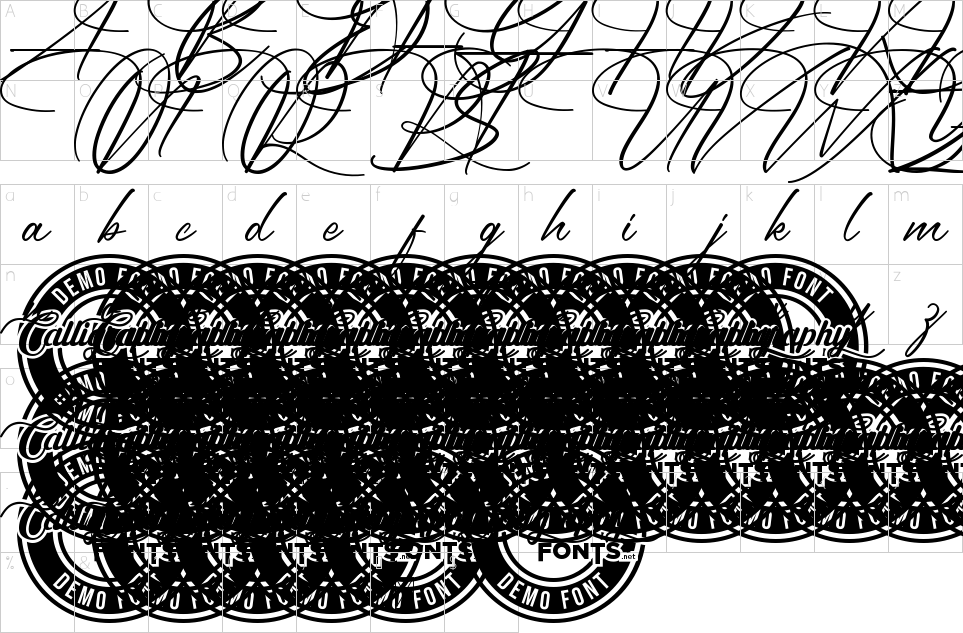
Glamour Line Font
Descubra a Glamour Line Font, uma elegante e sofisticada escolha para estilos de design que exigem charme e feminilidade. Esta fonte foi projetada por CalligraphyFonts e oferece um toque único capaz de enriquecer suas criações. Com 2,583 downloads até o momento, ela já é uma opção popular entre os designers gráficos, buscando uma solução perfeita para seus trabalhos. Perfeita para headlines, títulos e qualquer elemento que exija um toque moderno e atemporal, a Glamour Line traz sutileza em cada caractere. Suas linhas leves e elegantes permitem uma expressão de estilo único sem perder o respeito pela legibilidade necessária ao uso comercial ou personalizado. Engajue-se no design com essa fonte para criar projetos que chamam a atenção e deixem sua marca na web e em seus trabalhos impressos.
Mapa de caracteres da fonte Glamour Line Font